Мне очень нравится советская эстетика, особенно дизайн того времени. В своем проекте я решила создать марки, посвященные советским шрифтам. Всего я выбрала 15 шрифтов, каждому посвящены две марки: одна из них демонстрирует сам шрифт, на другой написан рандомно выбранный советский слоган.
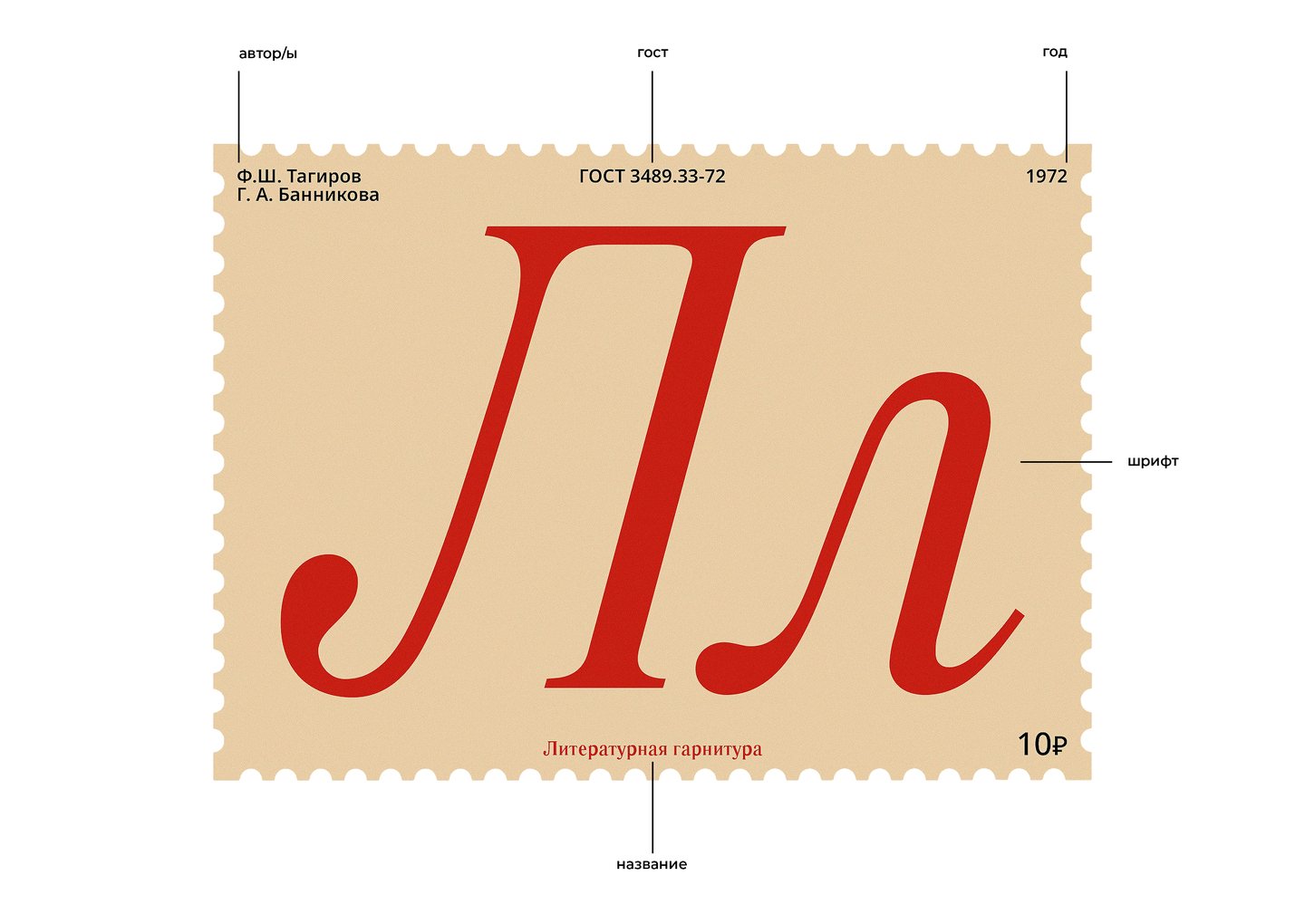
1. Литературная гарнитура 2. Агат гротеск 3. Елизаветинская гарнитура 4. Букварная гарнитура 5. Бодони книжная 6. Октябрьская гарнитура 7. Бажановская гарнитура 8. Обыкновенная новая 9. Банниковская гарнитура 10. Гарнитура Лазурского 11. Гарнитура Кузаняна 12. Гарнитура Ладога 13. Гарнитура Баченоса 14. Гарнитура Балтика 15. Гарнитура Телингатера